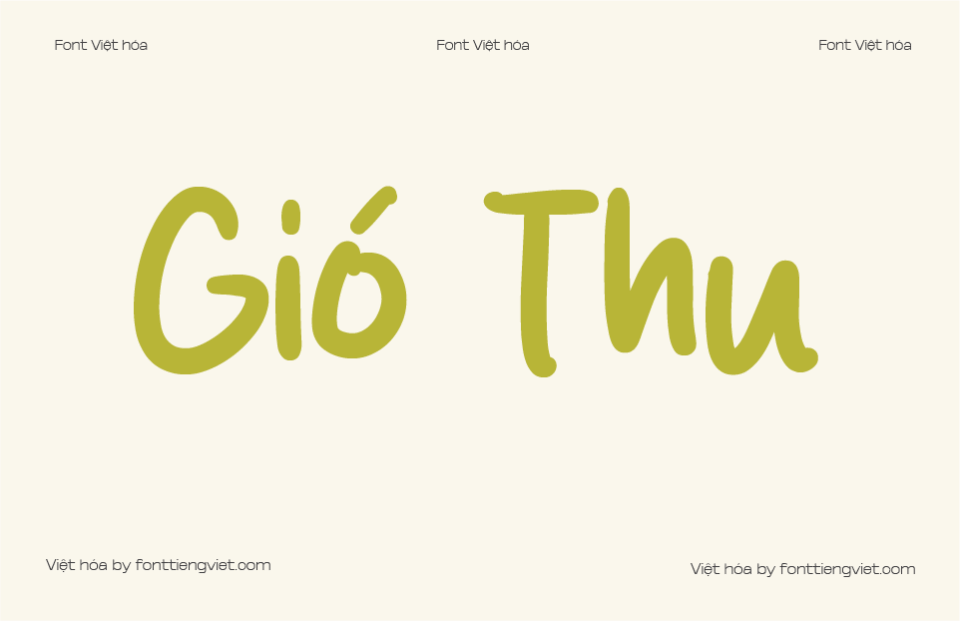
Tối Ưu Hóa Thiết Kế Với Font Việt hóa 1FTV VIP Shell Crabs Độc Đáo
Trong kỷ nguyên số, Font Chữ không chỉ là công cụ truyền tải thông tin mà còn là yếu tố then chốt tạo nên ấn tượng thị giác cho bất kỳ dự án nào, từ bài thuyết trình học đường cho đến các chiến dịch marketing chuyên nghiệp. Đối với cộng đồng thiết kế đồ họa, đặc biệt là học sinh, sinh viên đang tìm kiếm sự khác biệt, một bộ font độc đáo và chất lượng là vô cùng cần thiết. Hôm nay, chúng ta sẽ đi sâu vào khám phá sự đặc biệt của bộ Font Việt hóa 1FTV VIP Shell Crabs – một lựa chọn tuyệt vời mang đến sự mới mẻ và tinh tế cho các ấn phẩm của bạn. Sự kết hợp giữa phong cách nghệ thuật độc đáo và khả năng hiển thị tiếng Việt hoàn hảo đã biến 1FTV VIP Shell Crabs thành một tài sản quý giá mà bạn không nên bỏ qua khi làm việc trên máy tính.
Giới Thiệu Chi Tiết Về Font Việt hóa 1FTV VIP Shell Crabs
Bộ font 1FTV VIP Shell Crabs ban đầu đã nổi tiếng trong cộng đồng typography nhờ vào phong cách thiết kế riêng biệt, thường được mô tả là sự pha trộn giữa nét cổ điển và hiện đại, mang lại cảm giác mạnh mẽ nhưng không kém phần mềm mại. Tuy nhiên, như nhiều font quốc tế khác, phiên bản gốc thường gặp khó khăn trong việc hiển thị đầy đủ và chuẩn xác các ký tự tiếng Việt (như dấu thanh, chữ cái có dấu mũ). Đây chính là lúc quá trình Việt hóa phát huy tác dụng. Việc Việt hóa không chỉ đơn thuần là thêm các dấu mà còn là quá trình điều chỉnh khoảng cách, độ cao và sự hài hòa tổng thể của các ký tự để văn bản tiếng Việt trông tự nhiên và chuyên nghiệp nhất. Đối với học sinh cấp ba đang chuẩn bị các dự án nghiên cứu hay sinh viên đang thực hiện đồ án tốt nghiệp, việc sử dụng một font chữ được Việt hóa hoàn chỉnh như 1FTV VIP Shell Crabs giúp bài làm của họ tăng thêm tính thẩm mỹ và dễ đọc hơn rất nhiều.
Đặc Điểm Nổi Bật Của Bộ Font Này
Điều làm nên sự khác biệt của 1FTV VIP Shell Crabs chính là những đường nét táo bạo nhưng vẫn giữ được sự rõ ràng, không gây rối mắt. Font này đặc biệt phù hợp với các tiêu đề lớn, logo, hoặc các ấn phẩm đòi hỏi sự chú ý cao. Trong ngành giáo dục, việc tạo ra các tài liệu học tập, poster thông báo với font chữ ấn tượng sẽ giúp thu hút sự quan tâm của học sinh, sinh viên hơn. Các nhà thiết kế chuyên nghiệp cũng thường xuyên tìm kiếm các font VIP để đảm bảo tính độc quyền và sự khác biệt cho các thương hiệu mà họ xây dựng. Bộ font này được tối ưu hóa để tương thích với nhiều phần mềm thiết kế phổ biến như Adobe Photoshop, Illustrator, và các trình soạn thảo văn bản thông thường, giúp người dùng dễ dàng tích hợp vào quy trình làm việc hiện tại của mình.
Lợi Ích Của Bản Việt Hóa Cho Người Dùng Việt Nam
Bản Việt hóa của 1FTV VIP Shell Crabs giải quyết triệt để vấn đề lỗi font phổ biến. Người dùng tại Việt Nam, dù là giáo viên soạn giáo án, học sinh làm bài tập lớn, hay các nhà phát triển nội dung, đều cần một công cụ typography đáng tin cậy. Khi sử dụng font đã được Việt hóa kỹ lưỡng, bạn có thể hoàn toàn yên tâm về chất lượng hiển thị của các chữ cái như “ă, â, đ, ê, ô, ơ, ư” và các dấu thanh phức tạp. Điều này đặc biệt quan trọng trong các tài liệu chuẩn bị cho kỳ thi tốt nghiệp trung học phổ thông hoặc các văn bản chính thức cần sự chỉn chu tuyệt đối. Bản Việt hóa đảm bảo rằng thông điệp của bạn được truyền tải một cách trọn vẹn và không bị hiểu nhầm do lỗi hiển thị.
Ứng Dụng Thực Tế Cho Các Dự Án Sáng Tạo Cá Nhân và Học Thuật
Font Việt hóa 1FTV VIP Shell Crabs có tính linh hoạt cao, phù hợp với nhiều mục đích sử dụng khác nhau. Đối với học sinh, sinh viên, đây là lựa chọn lý tưởng cho các poster dự án khoa học, bìa tiểu luận, hay các infographic trình bày kiến thức. Sự độc đáo của nó giúp bài làm của bạn nổi bật giữa đám đông, thể hiện sự đầu tư nghiêm túc vào mặt hình thức. Đối với các nhà thiết kế đồ họa, font này có thể được ứng dụng để tạo ra các tiêu đề báo chí điện tử, thiết kế bao bì sản phẩm cao cấp, hoặc các ấn phẩm mang tính nghệ thuật. Việc sở hữu một bộ font “VIP” và hiếm giúp bạn nâng cao chất lượng dịch vụ và thu hút khách hàng tiềm năng. Nó không chỉ là một công cụ mà còn là một tuyên ngôn về phong cách thiết kế.
- Thiết Kế Thương Hiệu: Tạo logo và nhận diện thương hiệu độc đáo.
- Xuất Bản: Sử dụng cho tiêu đề sách, tạp chí, đặc biệt là các ấn phẩm nghệ thuật.
- Học Thuật: Làm nổi bật các điểm quan trọng trong bài thuyết trình và luận văn.
- Đồ Họa Web/Social Media: Tạo hình ảnh bắt mắt, thu hút lượt tương tác cao.
Tóm lại, Font Việt hóa 1FTV VIP Shell Crabs là một tài nguyên thiết kế vô giá, mang lại sự kết hợp hoàn hảo giữa thẩm mỹ quốc tế và sự tối ưu hóa cho ngôn ngữ tiếng Việt. Dù bạn là học sinh đang khao khát có một bài thuyết trình ấn tượng, sinh viên đang hoàn thiện đồ án, hay một chuyên gia thiết kế đang tìm kiếm sự khác biệt, bộ font này chắc chắn sẽ là một trợ thủ đắc lực. Đầu tư vào chất lượng typography chính là đầu tư vào hiệu quả truyền thông. Việc lựa chọn một Font Chữ đẹp và chuẩn Việt hóa sẽ nâng tầm mọi dự án của bạn lên một đẳng cấp mới, giúp bạn tự tin hơn trong công việc và học tập. Hãy khám phá và trải nghiệm sức mạnh của 1FTV VIP Shell Crabs ngay hôm nay để thấy sự khác biệt!